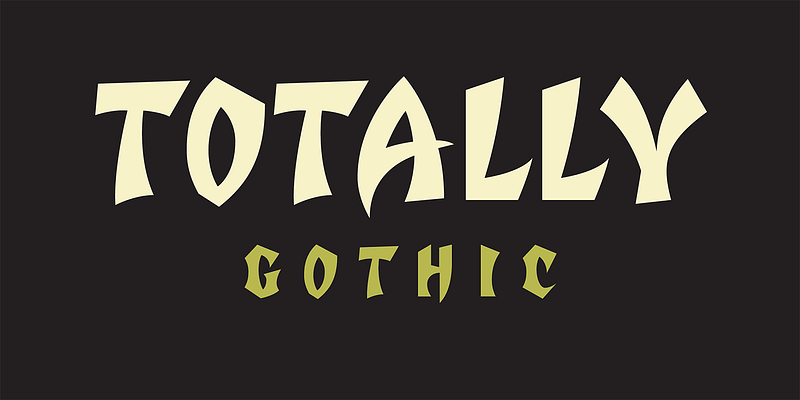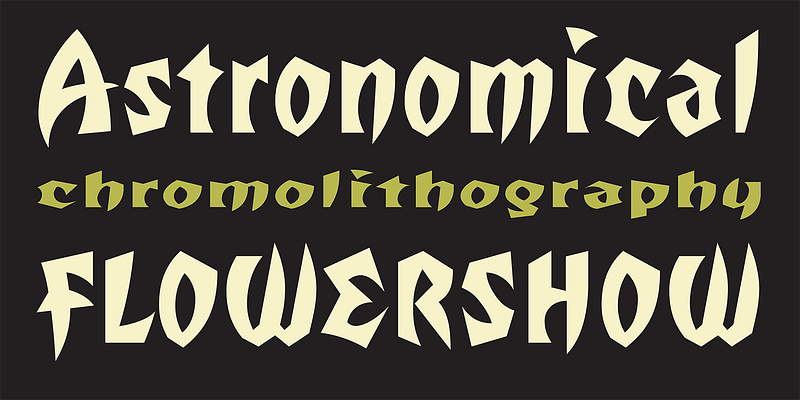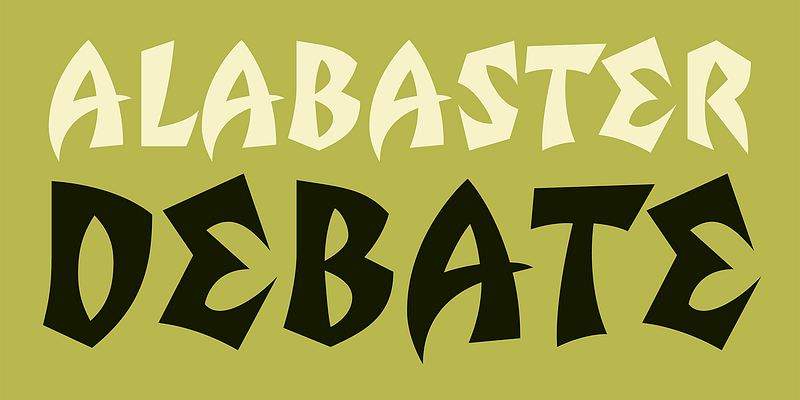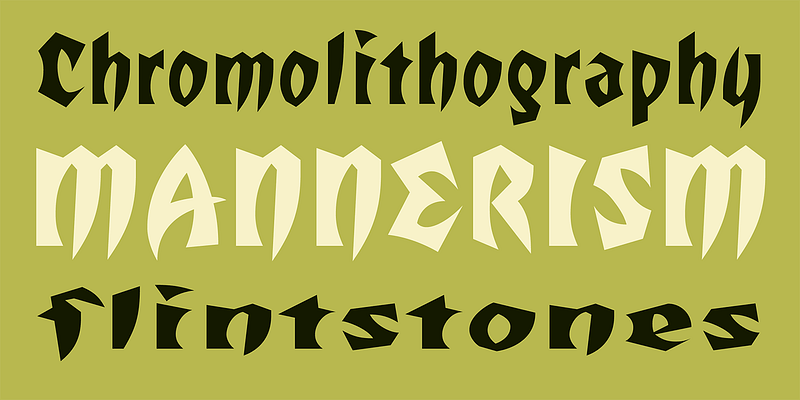
Totally Gothic è l’interpretazione del XX secolo dello stile di lettere nere di Zuzana Licko. Come per molti dei suoi primi design, Totally Gothic è partito da una bitmap. A quei tempi, le bitmap con alias erano all’avanguardia e lei ne stava sperimentando le possibilità. Uno di questi esperimenti è iniziato come una bitmap di lettere nere che di per sé non era così interessante, ma quando ha applicato i contorni PostScript attorno ai caratteri tracciandoli automaticamente sono state generate diverse forme sorprendenti. L’essenza di queste forme è diventata la base per il design Totally Gothic.